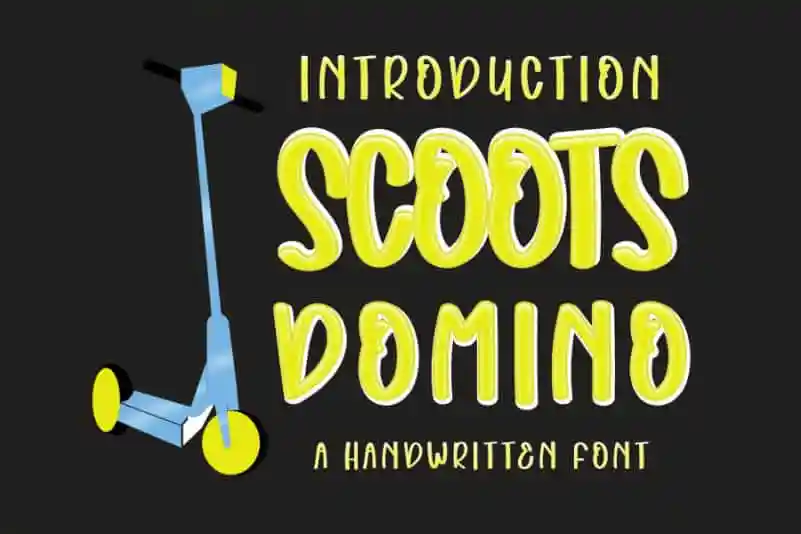
Scoots Domino Display Font – Download Grátis
A Scoots Domino Display Font é uma escolha perfeita para quem busca uma fonte escrita a lápis que mantém sua elegância clássica enquanto se atualiza e se torna fresca. Esta fonte não apenas é ideal para criatividades como cartazes de letras ou títulos, mas também se destaca em papelaria, tornando-a uma opção versátil e inovadora. Com seu estilo agradável e facilidade na aplicação, ela se adapta a um vasto range de ideias criativas. Seja você designer gráfico ou editor de conteúdo digital, esta fonte será uma adição perfeita ao seu arsenal de recursos gráficos, prometendo um visual moderno e único em qualquer projeto.